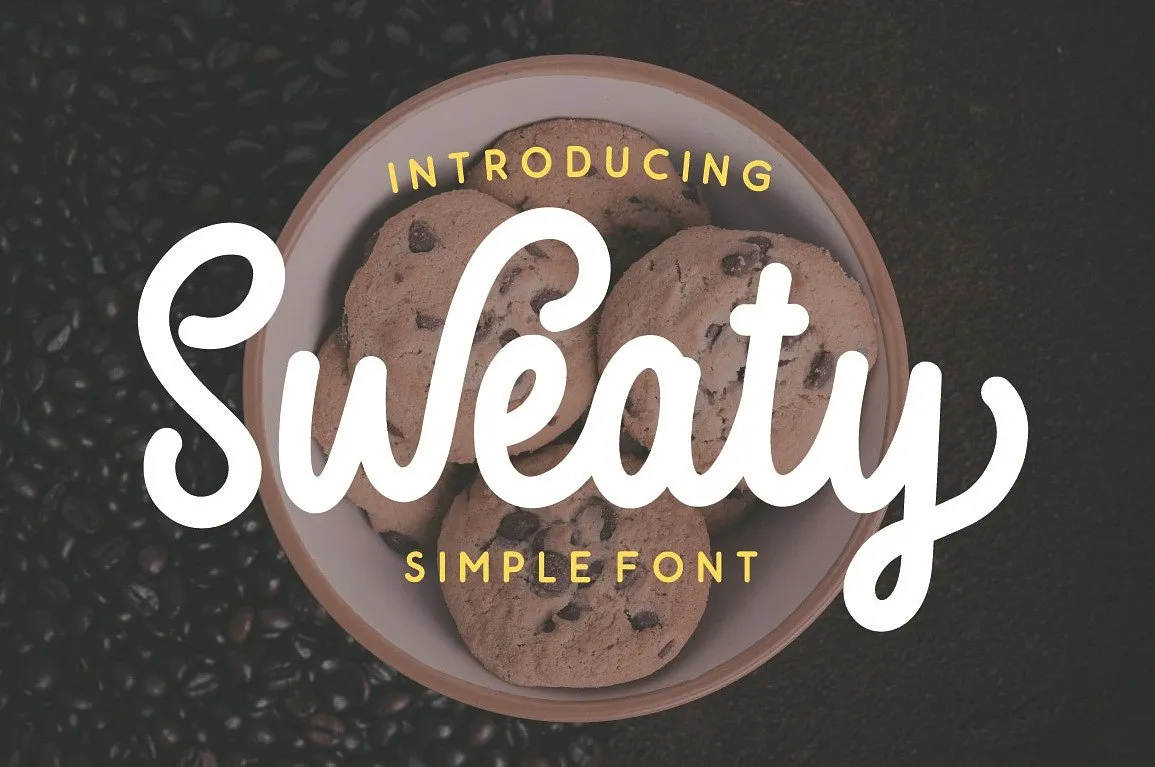
Sweaty Script Font – Download Grátis
Introduzimos a Sweaty Script Font! Desenhada por windestrian, esta fonte é uma tipografia script simples e divertida. Ideal tanto para logomarca, como para estampas de roupas ou cartões de convite de casamento, essa fonte tem uma cara engraçada que se torna perfeita para qualquer aplicação que você possa imaginar. O designer Hamilton criou a Sweaty Script Font inspirado no estilo deslumbrante e descontraído dos rolos humedados, um pouco do humor suave e da simplicidade de uma letra escrita à mão. Essa fonte combina bem em várias idéias de arte gráfica, seja como um logo chamativo ou textos personalizados para aplicativos mais íntimos. Com sua alternativa única, você pode criar qualquer tipo de desenho que desejar. Agora é a hora de dar vida à sua criatividade com a Sweaty Script Font e deixar seu design brilhar!